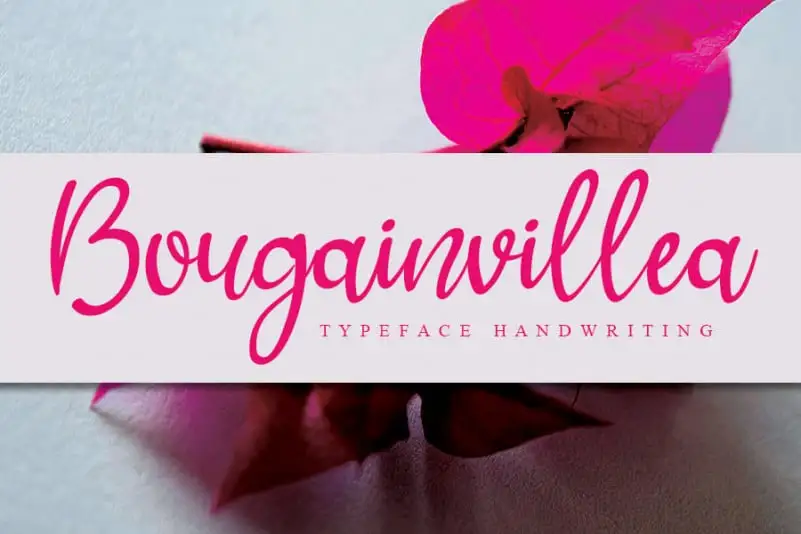
Bougainvillea Handwritten Font – Download Grátis
A ‘Bougainvillea Handwritten Font’ é uma delicada e elegante escrita à mão que se destaca por seu charme único. Perfeita para personalizar cartões de convite de casamento, cards de agradecimento, mensagens pessoais e até mesmo identidades visuais, esta fonte criativa ganha vida em todas as oportunidades onde uma pitada de escrita à mão é desejada. Suas linhas curvadas e suas nuances são ideais para adicionar um toque especial aos seus projetos gráficos, tornando cada projeto que usa essa fonte um verdadeiro trabalho de arte. Ideal tanto para seletivas cartas pessoais quanto para identidades corporativas sofisticadas, a ‘Bougainvillea Handwritten Font’ é o elemento perfeito para quem valoriza um estilo autêntico e delicado em suas criações digitais.